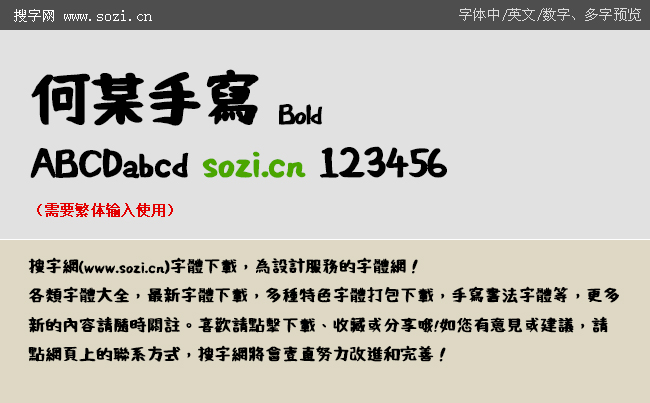
何某手寫-Bold
搜字網給大家提供一款何某手寫-Bold中文字體下載,何某手寫體是Max基于日本的おつとめフォント字體增補修改而成的一款隨心所欲的手寫體。與原作者的主要差異是調整部件寫法、新增中文字、增加為5個字重、增加一些符號。經過Max的增補,何某手寫體對簡體的字體支持也挺不錯的。適用于平面宣傳設計、網頁設計、海報設計等應用。